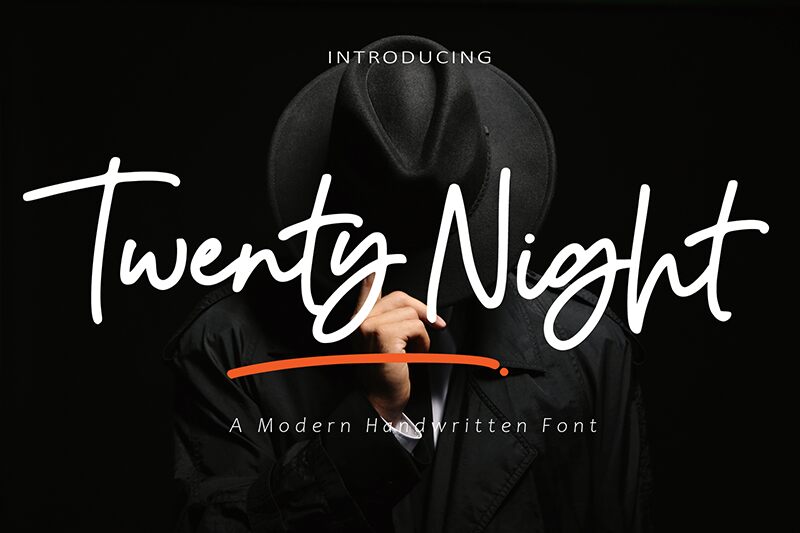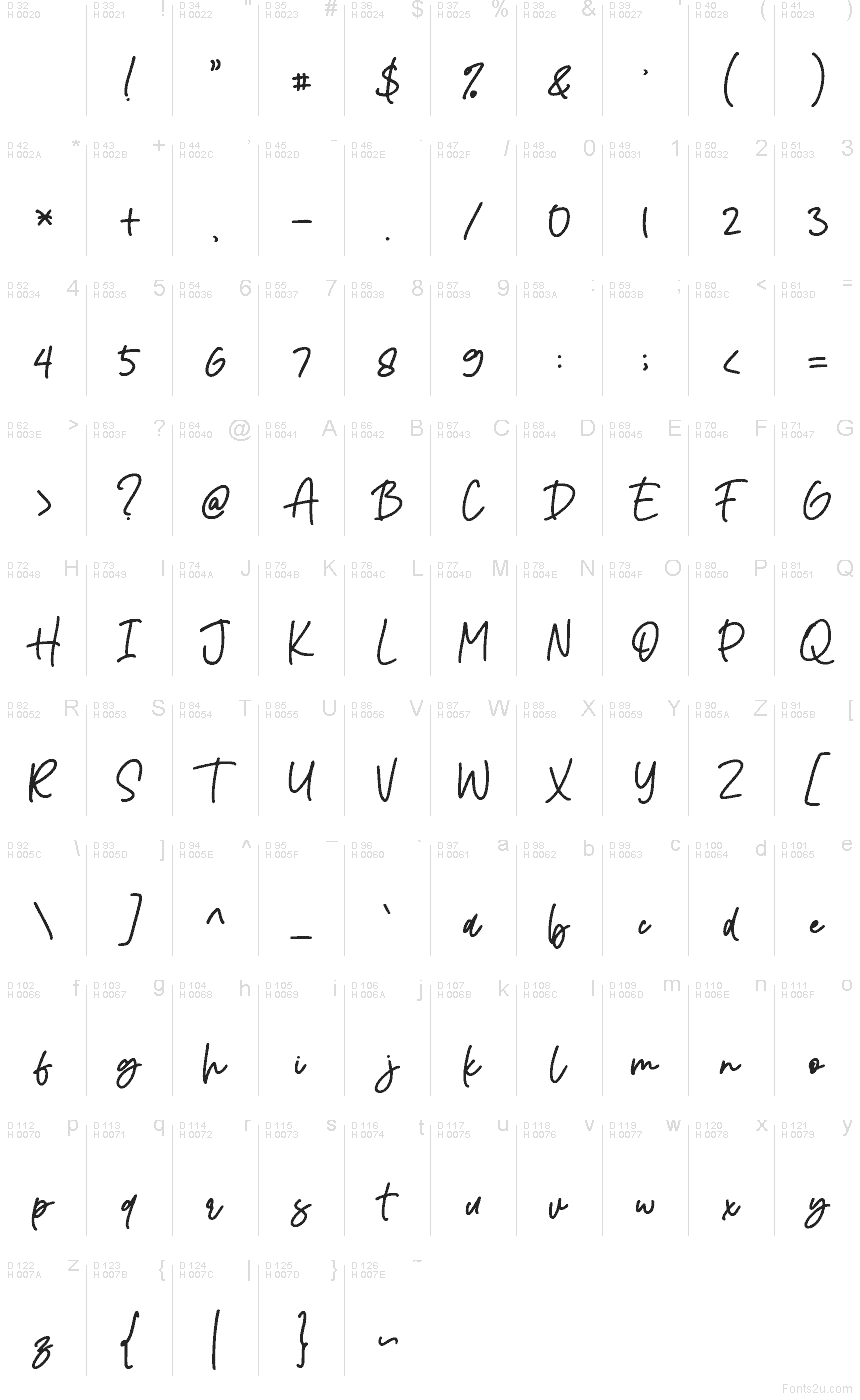
Twenty Night, di AMINMARIO, è un carattere scritto a mano gratuito con il fascino rilassato di un appunto notturno. Le lettere poggiano su tratti rapidi e decisi: le linee trasversali delle «t» si allungano ampiamente sopra la parola, mentre le lettere arrotondate mantengono uno stile informale, personale, quasi da taccuino.
Questo font gratuito è perfetto per il branding di caffè, candele e packaging lifestyle, e si adatta facilmente a titoli di poster, header per i social media, copertine e grafiche con citazioni brevi. Funziona al meglio dove serve un tocco umano e leggermente drammatico: grazie a quei lunghi tratti trasversali e al ritmo fluido, anche una frase breve sembra una linea scritta a mano.